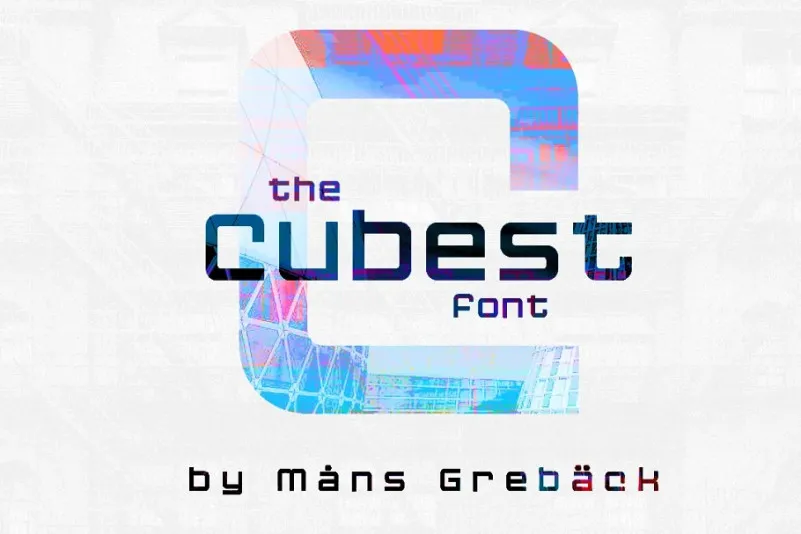
Cubest Font – Fonte Grátis
Cubest Font
Esta fonte sans-serif é uma criação elegante desenvolvida pela Mans Greback em 2021. Inspirada na junção de várias influências estilísticas, a Cubest Font apresenta um aspecto quadrado e linhas monolíticas que traz à tona um estilo retro-digital futurista. Perfeita para design gráfico moderno, sua simplicidade e arquitetura geométrica tornam-na uma opção ideal tanto para aplicações digitais quanto impressas, oferecendo flexibilidade e clareza necessárias em qualquer projeto visual. Seja você um designer ou editor de texto, a Cubest Font é uma escolha inteligente para suas necessidades, proporcionando o contraste único e moderno que sua peça requer.